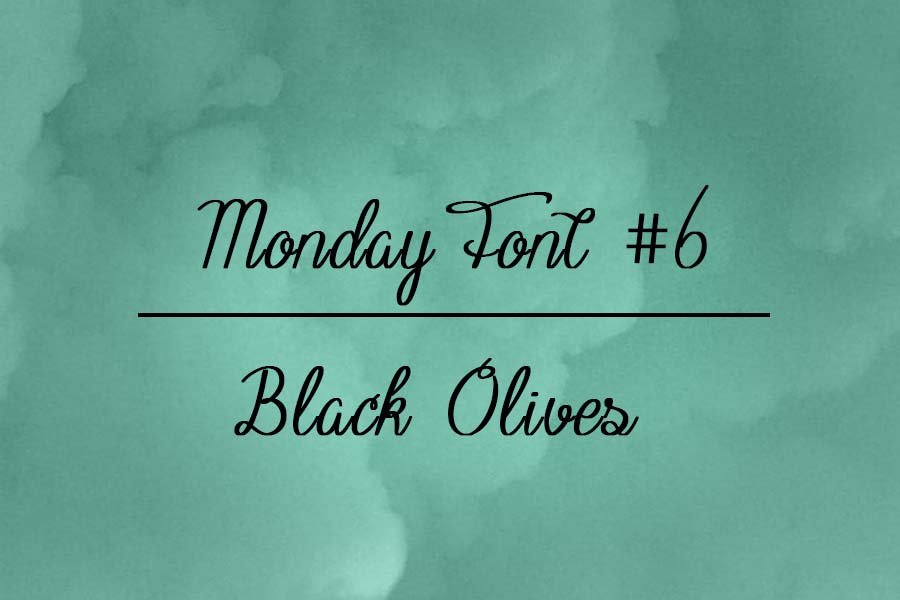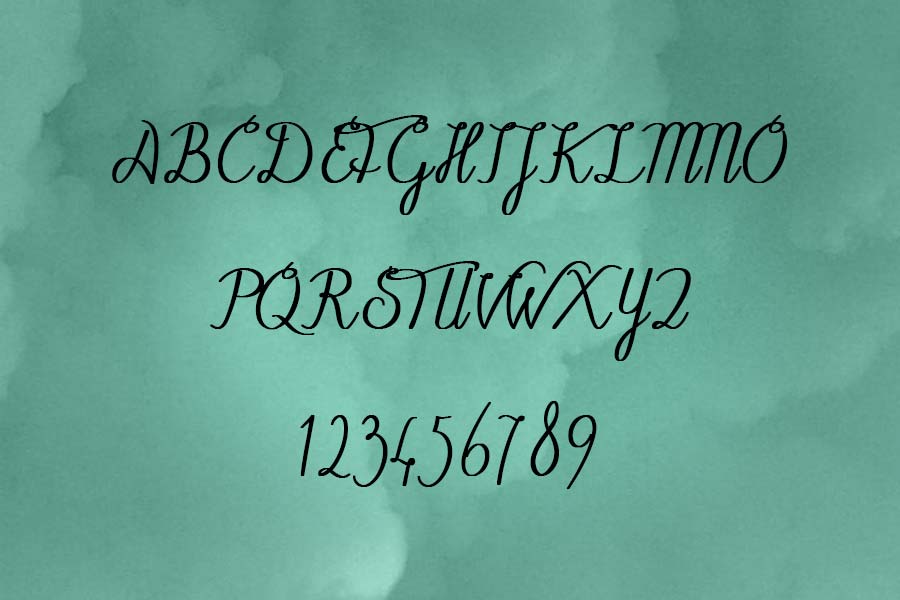
Cambiamos un poco el estilo de la fuente tipográfica de hoy. La elegida para hoy es Black Ollives, una tipografía manuscrita bastante maja, buen acabado y elegante. A por ella!